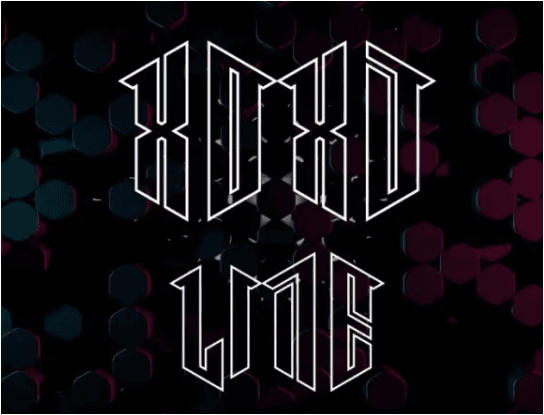
XoXdLine Font
Представляем наш новый продукт XoXdLine Font — Modern Font — это смелый и аутентичный дисплейный шрифт. Шрифт подходит для любого проекта брендинга, такого как логотип, печать на футболках, киберспорт и многое другое. выдающийся в широком диапазоне контекстов.